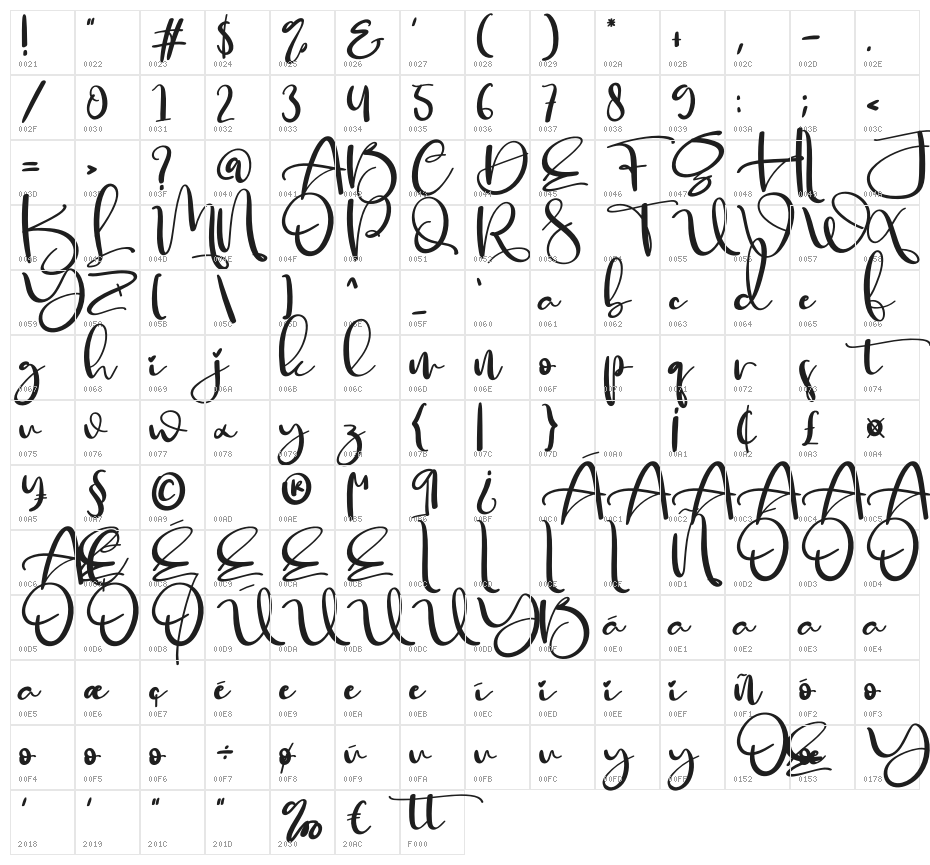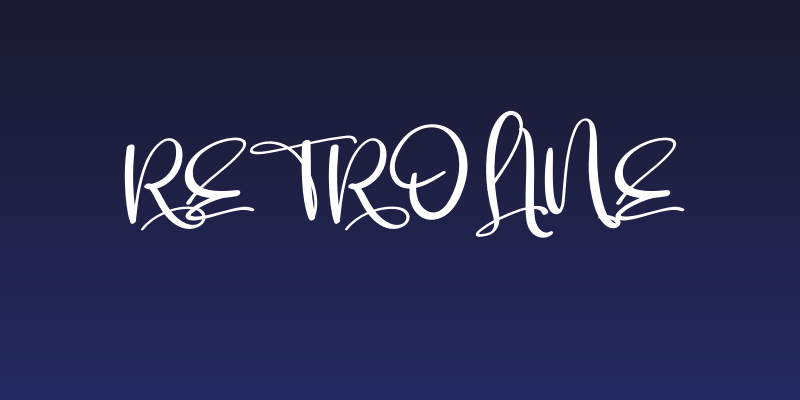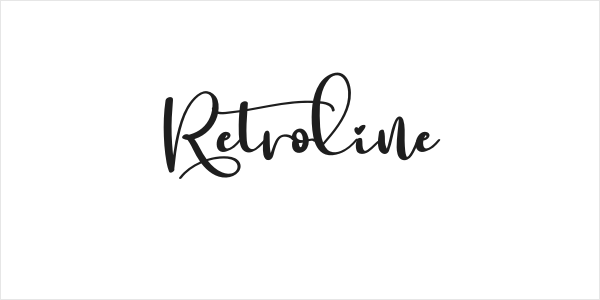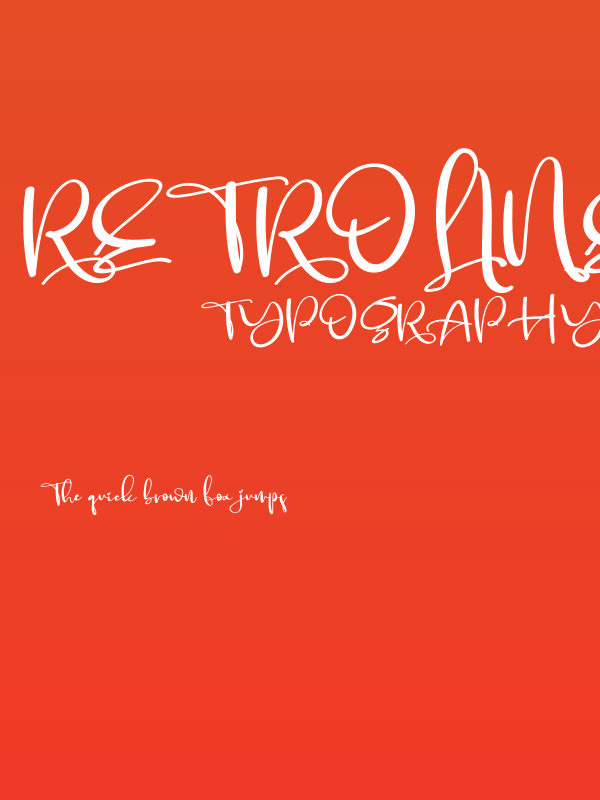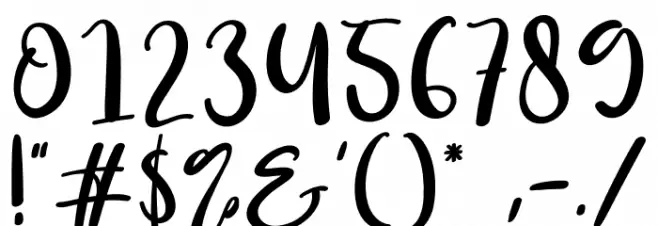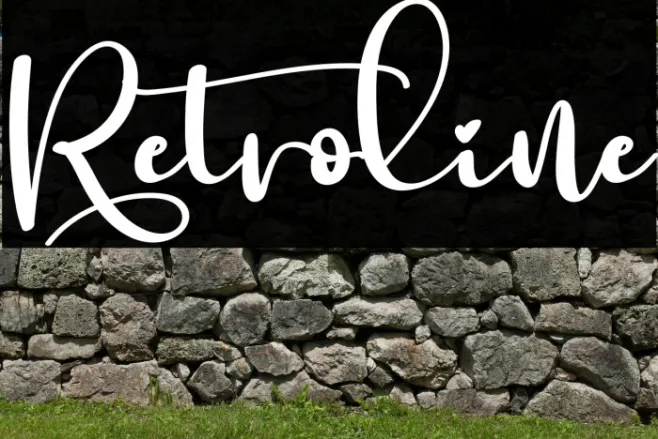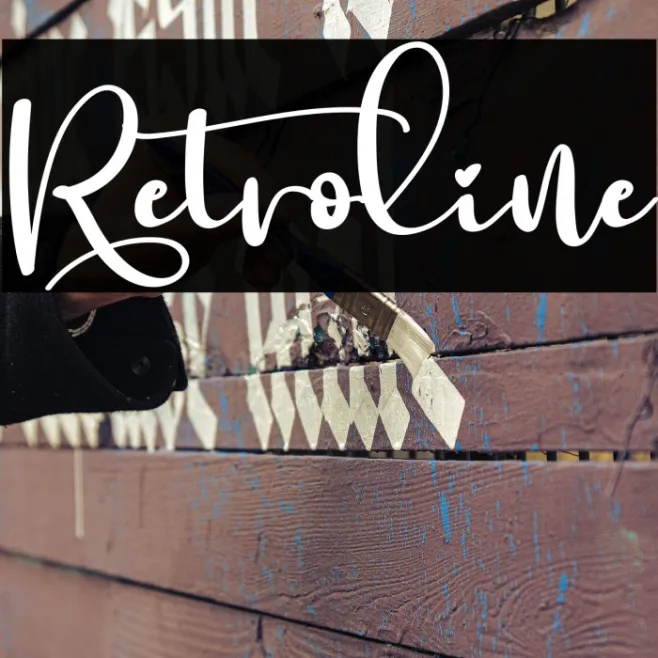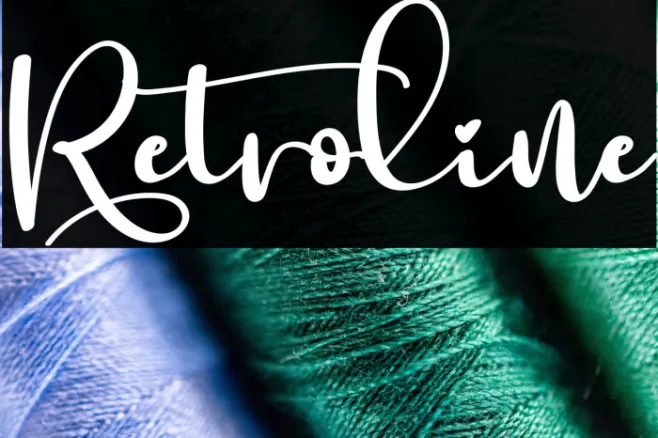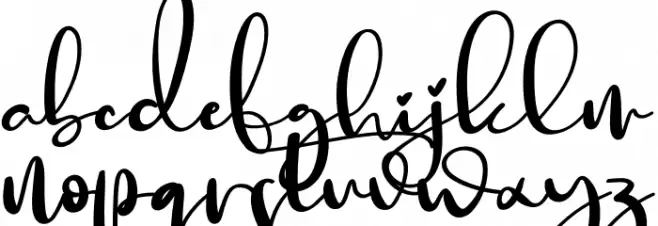
Retroline Font
| Cas d'utilisation | Logos, Invitations, Greeting cards |
| Projets proposés | Ideal for greeting cards, invitations, logos, and branding projects that require a personal and whimsical touch. |